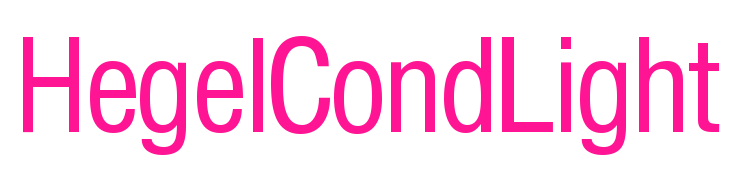
HegelCondLight 詳情頁(yè)
HegelCondLight字體字庫(kù)是一款讓人賞心悅目、百看不厭的英文字體,適合各類(lèi)廣告和產(chǎn)品包裝設(shè)計(jì)應(yīng)用,字體大小0.04MB,格式為ttf字體,上傳用戶(hù)是文生電腦,作者/版權(quán)方為未知